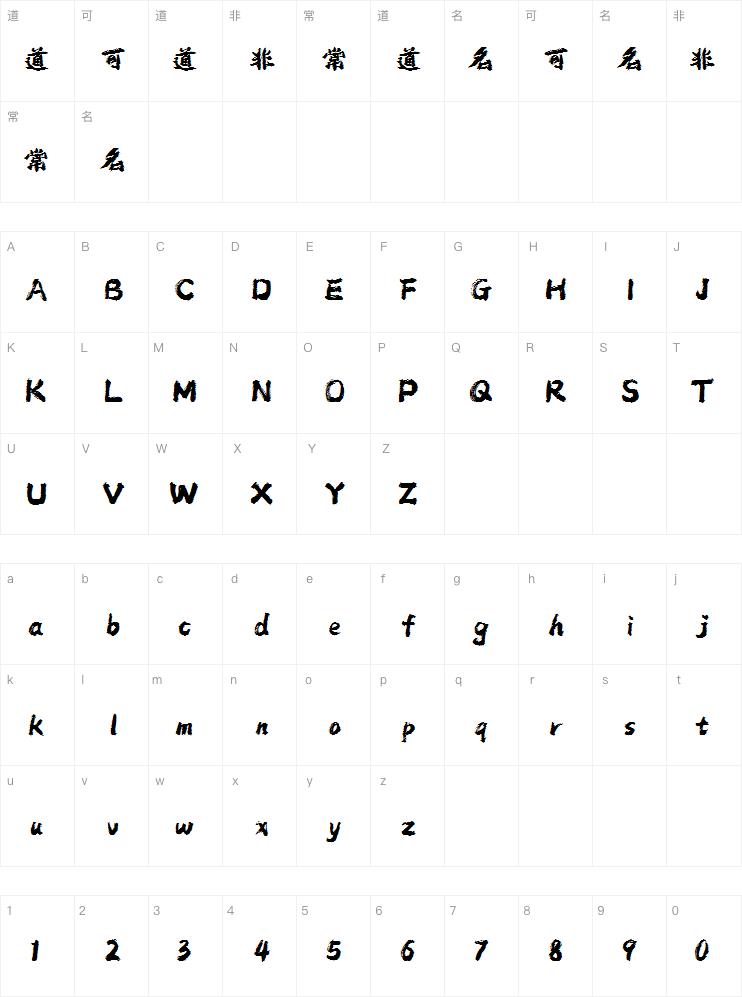
阿里汉仪顺利热土体
阿里汉仪顺利热土
字体在榜书特色中融入兰亭韵味,集金石篆刻与隶书风格。其浓厚国风韵味与视觉张力,唤起了万千国人对于家乡热土的情感归属。字体在行楷的字体基础上,强化兰亭的韵味风格并且进行榜书的特别点融合,加强律动笔势感受,在笔画转折的结点上通过飞白和枯笔的笔触进行动感的表现。
阿里汉仪顺利热土体